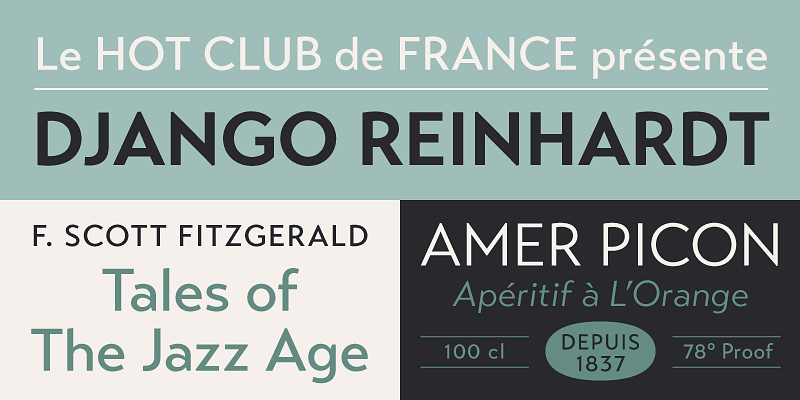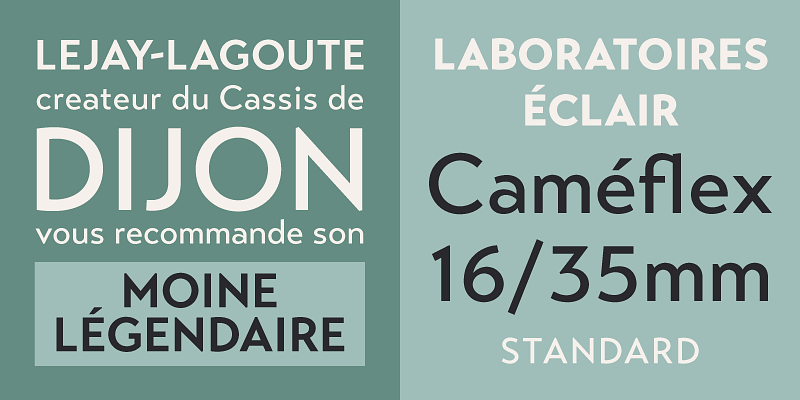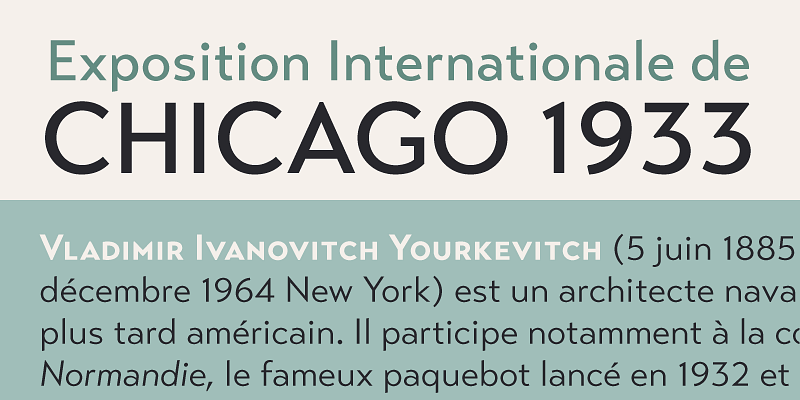
Transat Text est un frère plus rationnel de la police Art Déco « Transat », avec une hauteur d’œil légèrement supérieure et des largeurs de caractères plus régulières que son homologue, ce qui garantit un plus grand confort de lecture.